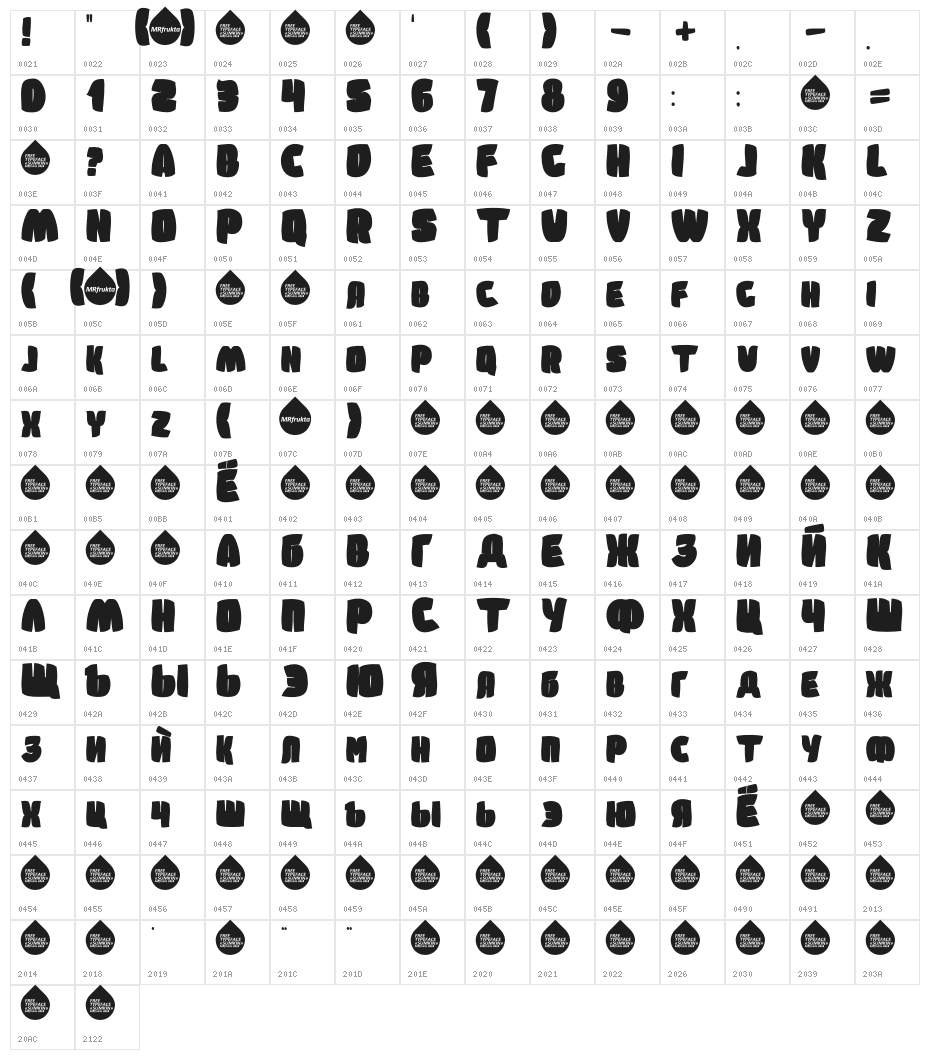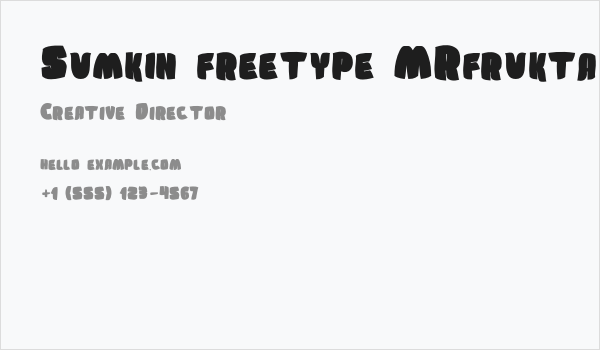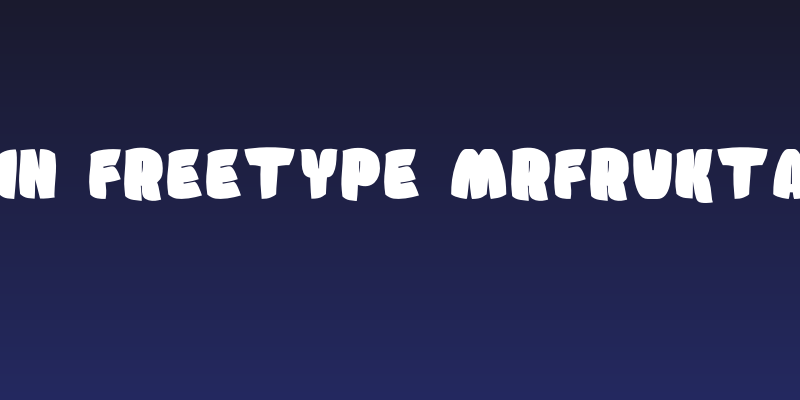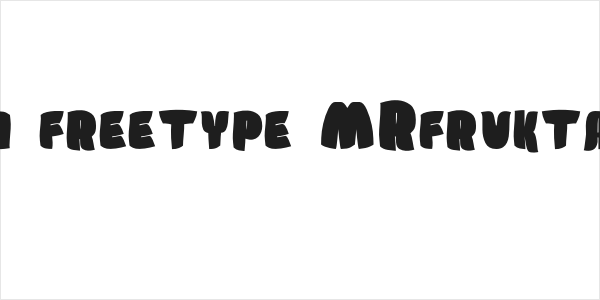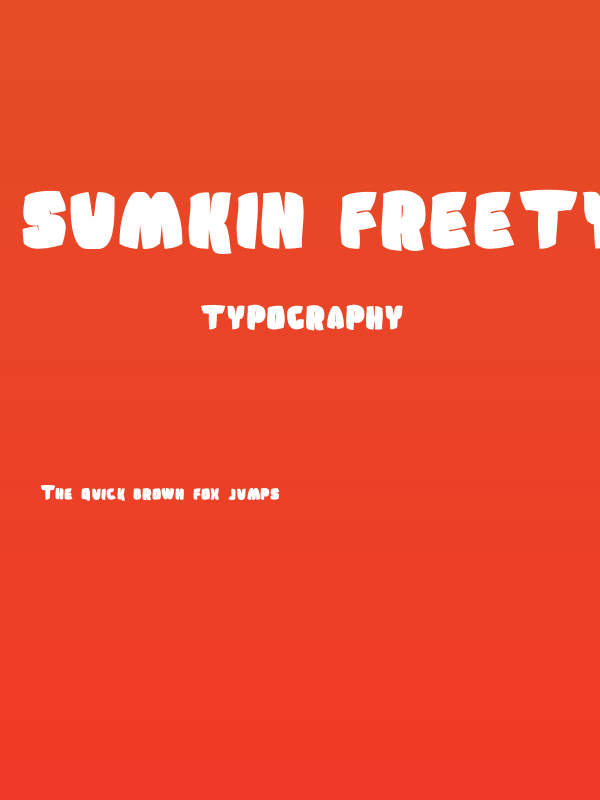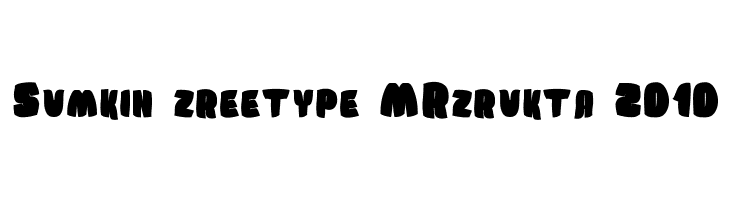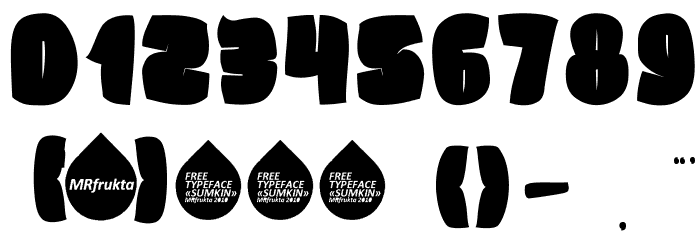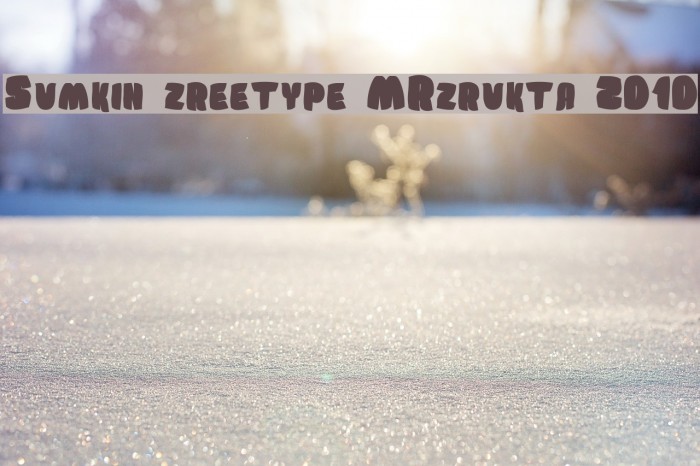
Sumkin freetype MRfrukta 2010 Font
| Style général | Vintage, Modern |
| Projets proposés | Ideal for posters, logos, children's book covers, and any project needing a fun, eye-catching typeface. |